싸인은 단순한 글씨가 아니라 나만의 개성을 담은 멋진 아이콘이 될 수 있어요. 유명 인사나 아티스트의 싸인을 보면 스타일리시하고 독창적이죠! 그렇다면 어떻게 하면 나도 세련된 싸인을 만들 수 있을까요? 이번 글에서 싸인 디자인의 핵심을 알려줄게요. ✍
싸인은 계약서, 팬 사인회, 예술 작품 서명 등 여러 상황에서 사용돼요. 단순한 이름을 넘어서 브랜드화된 느낌을 주려면 몇 가지 디자인 원칙을 따르는 게 중요하답니다. 이제부터 세련된 싸인을 만드는 방법을 하나씩 살펴볼게요!
세련된 싸인의 중요성
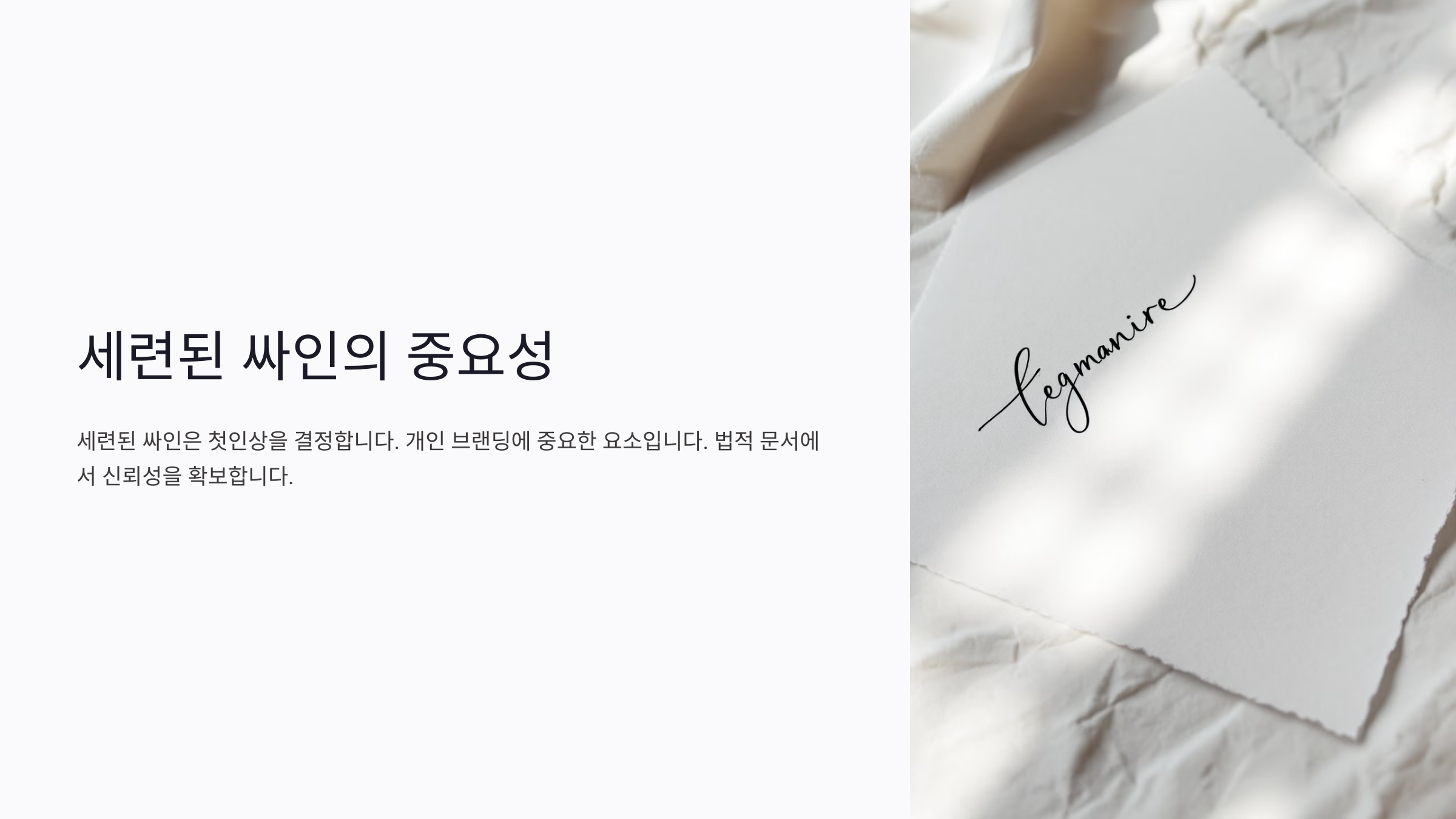
싸인은 단순한 서명이 아니에요. 어떤 사람인지, 어떤 인상을 남길지 결정하는 요소가 될 수 있죠. 예를 들어, 기업 대표의 싸인은 강렬하면서도 간결해야 하고, 연예인의 싸인은 개성 있고 독창적이어야 해요.
멋진 싸인은 첫인상을 강하게 남길 수 있어요. 실제로 유명 인사의 싸인은 팬들에게 하나의 작품처럼 여겨지기도 해요. 예를 들어, 스티브 잡스는 서명을 깔끔하고 단순하게 했지만, 그의 브랜드 이미지와 완벽하게 어울렸어요.
🔥 유명인의 세련된 싸인 특징 🔥
이름 싸인 스타일 특징 스티브 잡스 심플 & 미니멀 깔끔하고 명확한 필기체 마이클 잭슨 화려한 곡선 스타일리시한 필기체 김연아 부드러운 곡선 우아한 필기체 싸인은 단순히 글씨를 쓰는 게 아니라, 자기 자신을 표현하는 방법이에요. 멋진 싸인을 만들고 싶다면 자신의 스타일을 먼저 정해 보는 게 중요하죠! ✨
다양한 싸인 스타일
싸인 스타일은 사람의 성격과 개성을 반영해요. 단순한 싸인부터 예술적인 싸인까지 다양한 스타일이 존재한답니다. 어떤 스타일이 내게 어울리는지 살펴보고, 원하는 방향을 정하는 게 중요해요!
🎨 대표적인 싸인 스타일 4가지 ✍
스타일 설명 예시 미니멀 스타일 단순하고 깔끔한 디자인 스티브 잡스 곡선 스타일 부드럽고 자연스러운 곡선 사용 김연아 예술적 스타일 독특하고 창의적인 디자인 마이클 잭슨 이니셜 스타일 이니셜을 강조한 간결한 디자인 빌 게이츠 어떤 스타일이 마음에 드나요? 나는 개인적으로 곡선 스타일이 부드러우면서도 세련된 느낌이 있어서 좋아요! 😊
멋진 싸인 만드는 5단계
이제 본격적으로 세련된 싸인을 만드는 방법을 알아볼 차례예요! 아무리 예술적인 감각이 없어도, 아래 5단계를 따라 하면 누구나 멋진 싸인을 만들 수 있답니다. ✍
📝 1단계: 기본 형태 정하기 🏗
가장 먼저, 어떤 스타일의 싸인을 만들지 정해야 해요. 내 이름을 풀어서 쓸 건지, 이니셜만 활용할 건지 고민해 보세요. 싸인의 분위기 역시 결정해야 해요. 예를 들어, 클래식한 느낌을 원하면 필기체 스타일을, 모던한 느낌을 원하면 직선적인 스타일을 선택하는 게 좋아요.
✒ 2단계: 필기체 연습하기 🖋
싸인은 글씨체가 매우 중요해요. 필기체는 싸인을 더 유려하고 멋스럽게 보이게 해 줘요. 여러 필기체를 시도해 보면서 손에 익는 스타일을 찾아보세요. 특히, 유명한 서체를 참고하면 더욱 세련된 싸인을 만들 수 있어요.
🎭 3단계: 개성 있는 요소 추가하기 🎨
싸인에 나만의 개성을 담아야 해요. 예를 들어, 이름의 첫 글자를 강조하거나, 특정 문자를 길게 늘이는 것도 방법이에요. 일부 사람들은 싸인 끝에 작은 별 ✨이나 하트 💖를 추가하기도 해요.
🖍 4단계: 일관된 스타일 유지하기 🏁
싸인은 항상 일정한 형태를 유지해야 해요. 싸인이 너무 자주 변하면 공식적인 문서나 계약서에서 혼란을 줄 수 있어요. 연습하면서 손에 익도록 꾸준히 반복해 보세요.
🚀 5단계: 실전 연습 & 최적화 📜
이제 최종적으로 실전 연습을 해 볼 차례예요! 노트에 여러 번 반복해서 싸인을 써 보면서 속도와 정확도를 높여 보세요. 가장 만족스러운 디자인을 선택해 최종 싸인으로 정하면 끝! 🎉
🔍 멋진 싸인을 위한 필수 요소 🔍
요소 설명 가독성 읽기 쉽게 디자인하기 개성 나만의 독특한 스타일 추가 일관성 싸인의 크기와 스타일 유지 속도 빠르고 자연스럽게 작성 가능해야 함 이제 싸인을 디자인하는 기본적인 단계를 익혔어요! 😊 다음은 싸인을 더욱 세련되게 만들어 주는 유용한 도구들을 소개할게요! ⬇
싸인 제작에 유용한 도구
세련된 싸인을 만들기 위해서는 연습뿐만 아니라, 도구의 도움을 받는 것도 좋은 방법이에요! ✨ 요즘은 다양한 디지털 및 아날로그 도구를 활용해 더 멋진 싸인을 만들 수 있답니다. 아래에서 꼭 필요한 도구들을 소개할게요! 🔍
🖊 아날로그 싸인 연습 도구 📝
도구 설명 만년필 부드러운 필기체 연습에 적합 캘리그래피 펜 스타일리시한 곡선 연습 가능 연습 노트 꾸준한 연습을 위해 필수 💻 디지털 싸인 제작 도구 🖥
디지털 환경에서 싸인을 제작하면 더욱 정교하고 멋진 결과물을 얻을 수 있어요. 요즘은 태블릿을 활용해 싸인을 연습하는 사람도 많아요! 🖊
프로그램/앱 특징 Adobe Illustrator 벡터 기반으로 정교한 싸인 제작 가능 Procreate 태블릿에서 싸인 디자인 및 연습 Signature Maker 자동으로 다양한 싸인 스타일 생성 위 도구들을 활용하면 싸인을 더욱 세련되게 디자인할 수 있어요. ✍ 이제 싸인을 한층 더 멋지게 만들 수 있는 팁을 알아볼까요? ⬇
싸인을 더욱 세련되게 만드는 팁
멋진 싸인을 만들기 위해 기본적인 방법을 익혔다면, 이제는 한 단계 더 업그레이드할 차례예요! 🎨 싸인을 더욱 세련되게 만드는 실전 꿀팁을 소개할게요. ✍
✨ 1. 싸인의 크기와 비율 조절하기 📏
싸인의 크기는 너무 작거나 크지 않도록 적절한 비율을 유지하는 것이 중요해요. 글자의 높낮이를 맞추고, 서명 공간에 맞춰 자연스럽게 조정하는 연습이 필요하죠. 일반적으로, 싸인은 이름 길이의 2~3배 정도의 너비를 가지는 것이 가장 보기 좋아요.
🎭 2. 싸인에 개성 있는 요소 추가하기 🎨
싸인에 나만의 특징을 넣어보세요! 예를 들어, 이니셜을 강조하거나, 특정 글자를 길게 늘이는 것도 방법이에요. 배우 레오나르도 디카프리오는 'L'을 강하게 쓰는 스타일을, 마이클 조던은 싸인에 독특한 곡선을 추가하는 스타일을 사용했어요. ✨
🔄 3. 선의 흐름을 자연스럽게 만들기 🖊
싸인의 선이 너무 뚝뚝 끊기면 부자연스러워 보여요. 부드러운 곡선과 자연스러운 필체를 유지하는 것이 중요해요. 특히, 필기체 스타일을 연습하면 싸인이 더욱 세련되어 보일 수 있어요.
🚀 4. 싸인의 마무리 강조하기 💡
싸인의 마지막 부분을 강조하는 것도 좋은 방법이에요. 예를 들어, 마지막 글자를 길게 늘이거나, 밑줄을 추가하는 식으로 스타일을 살릴 수 있어요. 유명인들의 싸인을 보면, 대부분 마무리가 깔끔하고 인상적인 경우가 많아요. 🎭
🌟 5. 싸인의 균형 맞추기 📐
싸인의 전체적인 균형이 중요해요. 좌우가 너무 치우치거나, 특정 글자만 너무 커지면 조화롭지 않게 보일 수 있어요. 글자의 크기와 위치를 조절해 시각적으로 균형 잡힌 싸인을 만들어 보세요!
💎 세련된 싸인을 위한 필수 체크리스트 ✅
항목 체크 여부 이름의 특징이 잘 드러나는가? ✅ 필기체 또는 곡선이 자연스러운가? ✅ 싸인의 균형이 맞춰졌는가? ✅ 마무리가 깔끔한가? ✅ 위 체크리스트를 따라 하면 더 세련된 싸인을 만들 수 있어요! 💡 이제 유명인들의 싸인을 분석해 보면서 나만의 스타일을 완성해 볼까요? ⬇
유명인의 싸인 스타일 분석
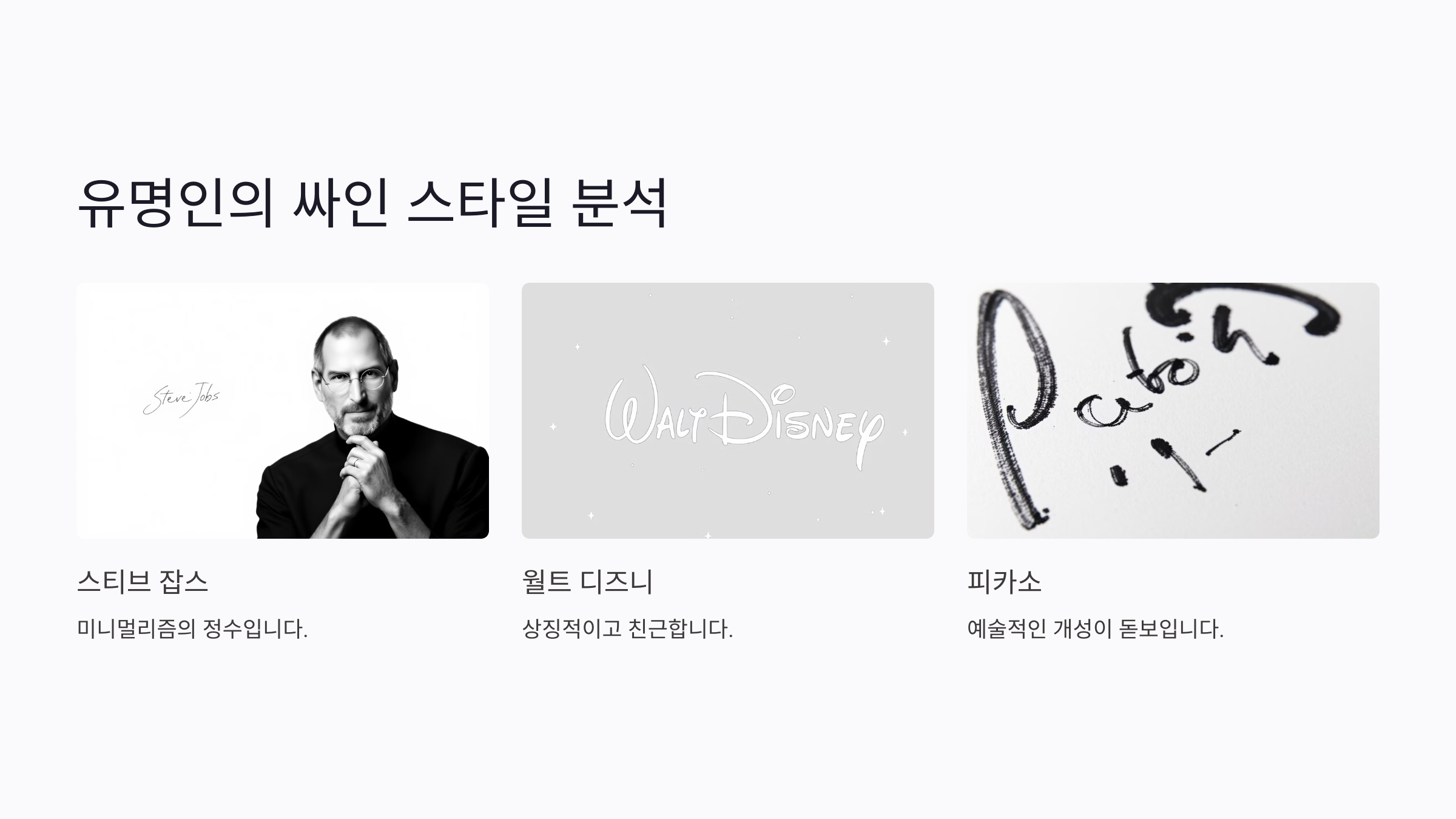
유명인의 싸인은 단순한 서명이 아니라 브랜드의 일부가 되기도 해요. 🎭 스타, 기업가, 운동선수 등 다양한 분야에서 활동하는 사람들의 싸인은 각자의 개성과 스타일을 잘 반영하고 있죠! ✍
💡 유명인의 싸인 스타일 3가지 🔍
이름 싸인 스타일 특징 스티브 잡스 미니멀 & 직선적 깔끔하고 심플한 디자인 마이클 잭슨 예술적 & 곡선 강조 스타일리시한 곡선 사용 김연아 우아하고 부드러운 스타일 곡선이 자연스럽고 안정감 있음 🔥 유명인의 싸인에서 배울 점 📝
유명인들의 싸인은 단순히 멋있어 보이는 것뿐만 아니라, 싸인하는 사람의 브랜드 이미지와 연결된다는 점이 중요해요. 예를 들어:
- 💡 스티브 잡스: 단순하고 직선적인 서명으로 그의 미니멀리즘 철학을 반영했어요.
- 💫 마이클 잭슨: 곡선을 강조하여 그의 예술적인 감각을 드러냈어요.
- ⛸ 김연아: 부드럽고 흐름이 자연스러운 서명으로 우아함을 표현했어요.
나도 이런 싸인을 만들고 싶다면? 이제 마지막으로 자주 묻는 질문(FAQ)과 함께 정리해 볼게요! ⬇
FAQ
Q1. 싸인을 멋있게 만드는 가장 중요한 요소는 무엇인가요?
A1. 싸인의 가장 중요한 요소는 가독성과 개성이에요! 읽기 쉬우면서도 나만의 독특한 스타일이 담겨야 해요. 곡선을 활용하거나, 이니셜을 강조하는 것도 좋은 방법이에요. ✍
Q2. 손글씨가 안 좋은데 싸인을 예쁘게 만들 수 있을까요?
A2. 물론이에요! 손글씨와 싸인은 별개예요. 필기체 연습을 하거나, 원하는 스타일을 따라 그리는 연습을 하면 충분히 멋진 싸인을 만들 수 있어요. 😊
Q3. 싸인을 만들 때 주의할 점이 있나요?
A3. 너무 복잡하게 만들면 실전에서 사용하기 어려울 수 있어요. 또한, 싸인의 크기와 균형을 맞추는 것도 중요해요. 쉽게 따라 할 수 있는지 꼭 확인하세요! 📏
Q4. 디지털 싸인을 만들려면 어떤 도구가 좋을까요?
A4. Adobe Illustrator, Procreate, Signature Maker 같은 프로그램을 활용하면 디지털 싸인을 쉽게 만들 수 있어요. 태블릿과 스타일러스 펜을 사용하면 더욱 정교한 싸인을 만들 수 있답니다! 💻
Q7. 싸인에 그림이나 아이콘을 넣어도 될까요?
A7. 네! 싸인에 작은 별, 하트, 밑줄 등을 추가하면 더욱 개성 있는 싸인이 돼요. 하지만 너무 복잡하면 실용성이 떨어질 수 있으니 적절하게 활용하세요. ⭐
Q8. 유명인의 싸인을 그대로 따라 해도 되나요?
A8. 참고하는 것은 좋지만 그대로 따라 하는 것은 추천하지 않아요! 유명인의 싸인에서 영감을 얻고, 나만의 스타일로 변형해서 만드는 게 좋아요. 🎭